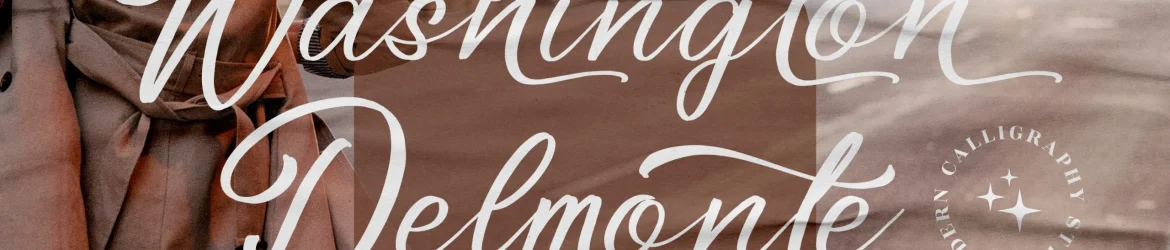
Washington Delmonte Font – Download Grátis
Washington Delmonte é uma elegante fonte de calligrafia moderna criada pelo estúdio Perspectype Studio. Esta premium signature font se destaca para qualquer projeto que precise de um toque especial, desde criações gráficas como logotipos e embalagens, até produtos domésticos e comunicação direta como cartões personalizados, sacolas shopping e etiquetas. Suas linhas clean e elegantes permitem uma grande versatilidade em diversos ambientes, garantindo um toque premium em qualquer projeto que você decida trabalhar com ela. Englobando desde embalagens gourmet até eventos especiais, Washington Delmonte é a escolha perfeita para quem busca personalizar seus projetos de forma única e sofisticada. Perspectype Studio é uma fontes designer famosa por criar soluções customizáveis que adaptam-se facilmente ao seu estilo. O uso desta fonte vai além do simples design gráfico; ela adiciona um brilho a qualquer projeto, oferecendo um toque de elegância e sofisticação. Não perca esta oportunidade para dar vida aos seus projetos com a delicadeza e sofisticação de Washington Delmonte Font.